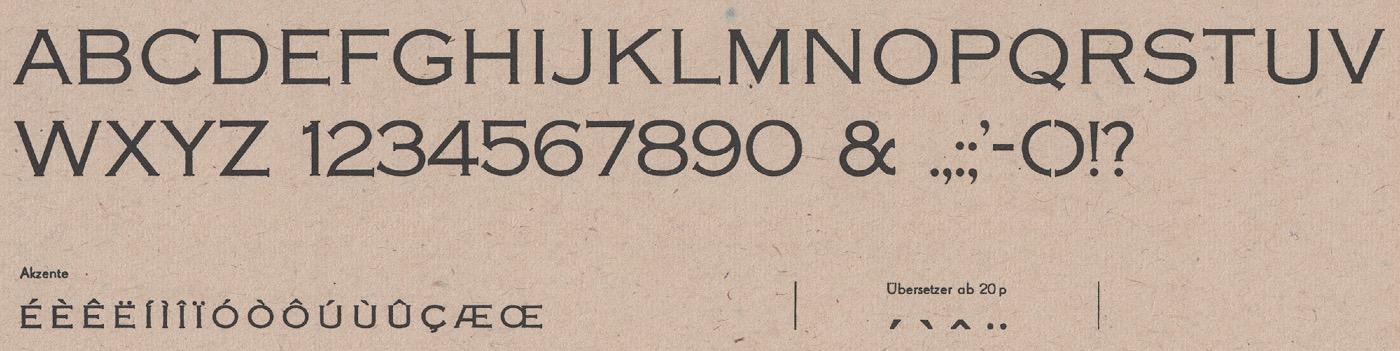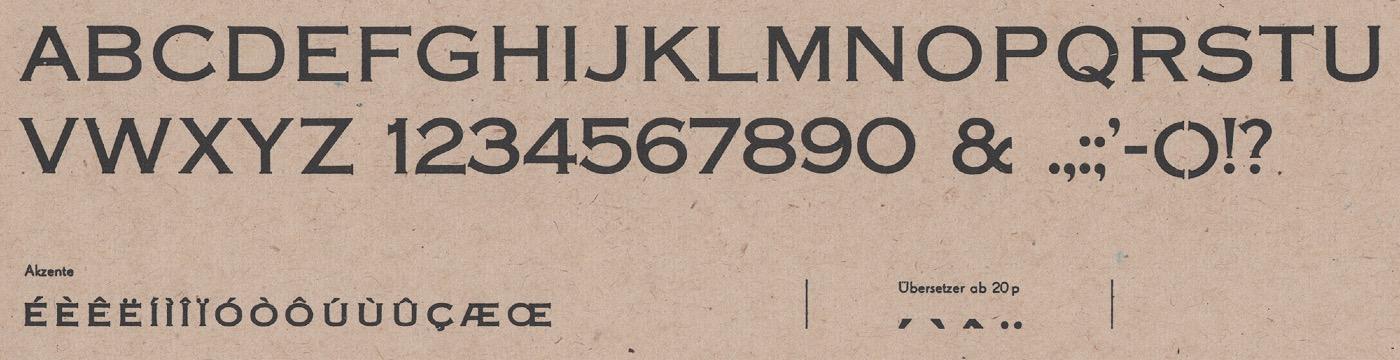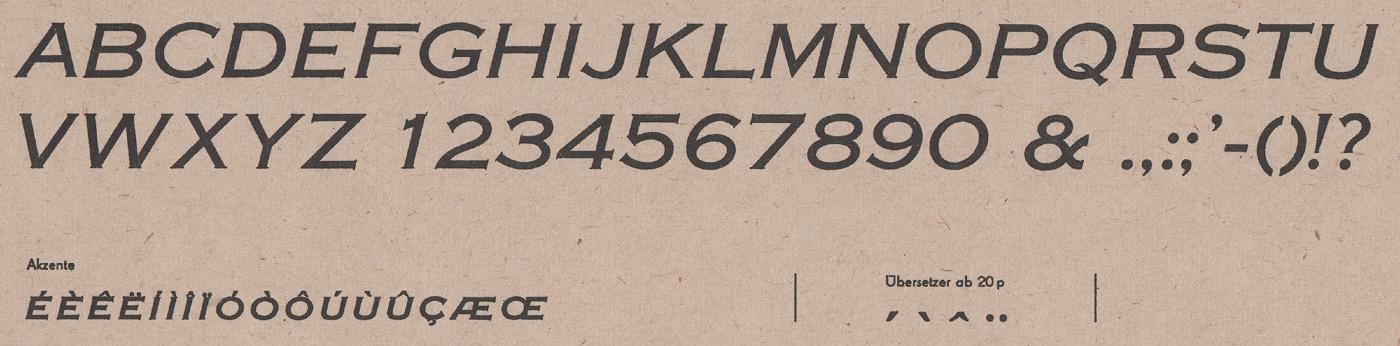
Die Mimosa war eine Bleisatzschrift im Fahrwasser der erfolgreichen Copperplate Gothic und erschien bei Schriftguß in Dresden bzw. in Partnerschaft bei C.E. Weber in Stuttgart. Zur Erstveröffentlichung finden sich widersprüchliche Angaben. Die drei Schnitte mager, halbfett und kursiv tauchen jedoch alle in Schriftmustern der 1920er-Jahre auf. In der DDR wurde die Schrift im VEB Typoart Dresden weiter angeboten.